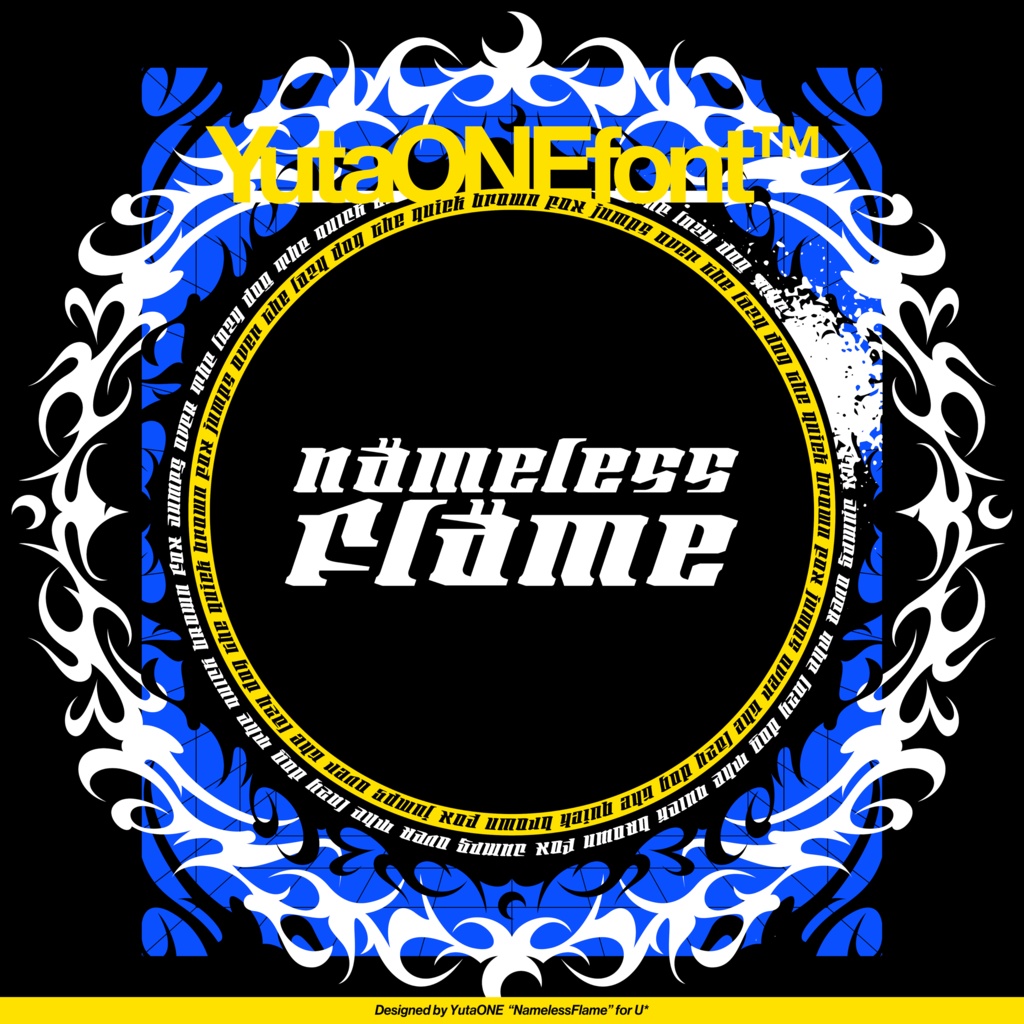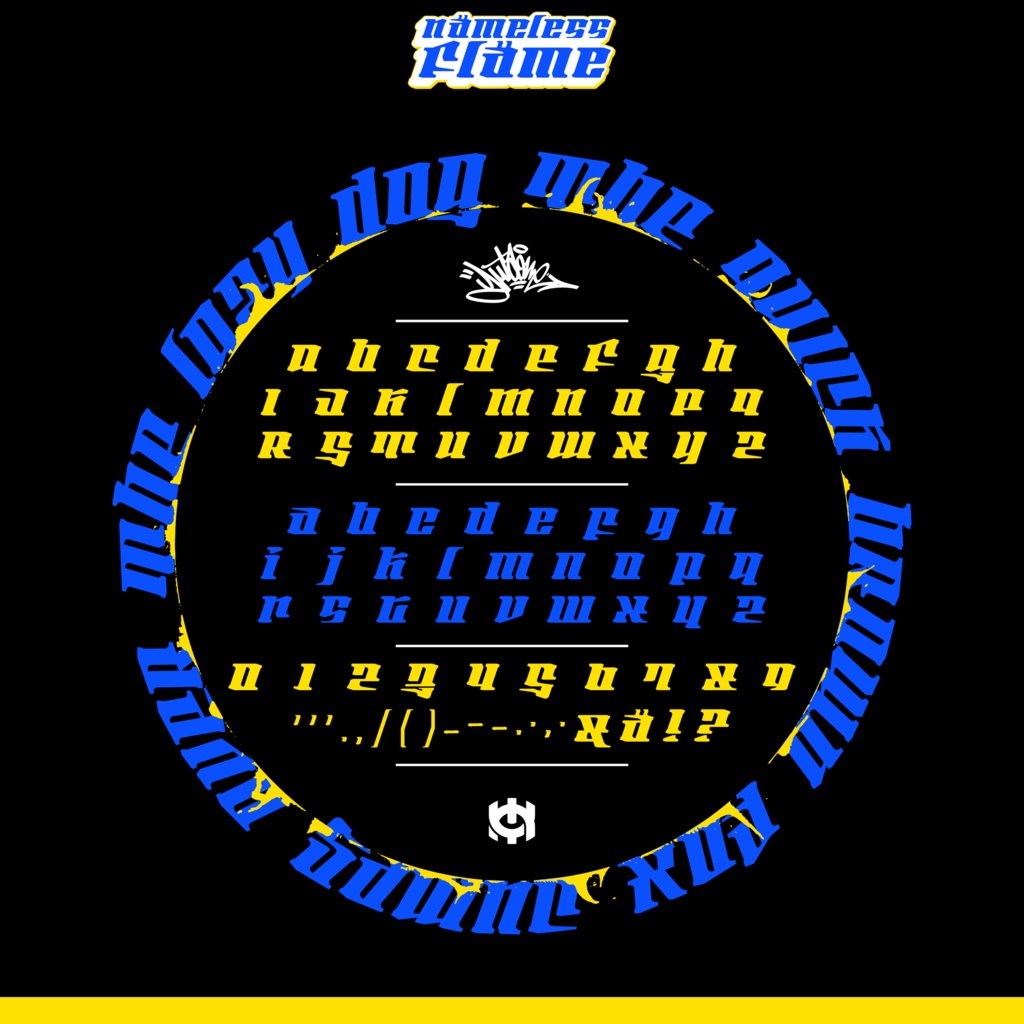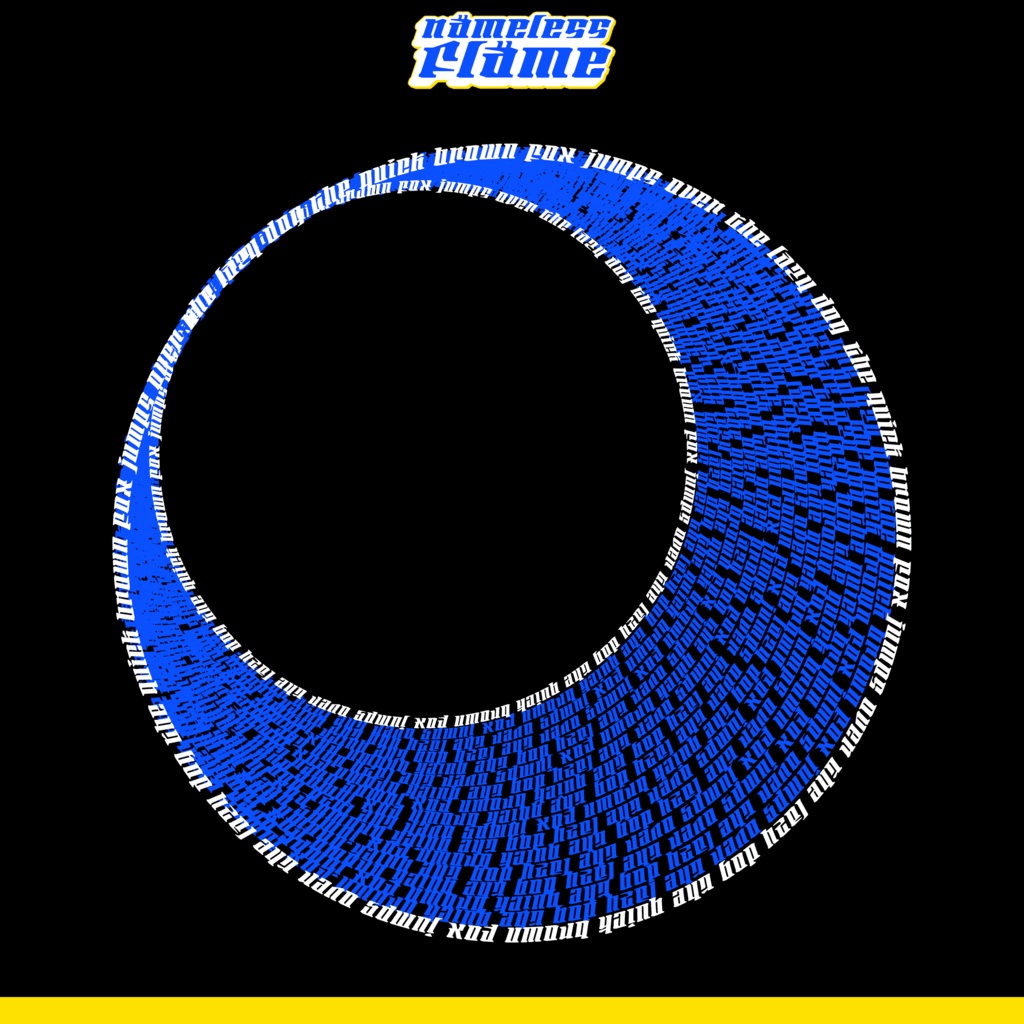
ネームレスフレイム(NamelessFlame)|Unnämed採用 タイプフェイス|ゆうたONEフォント™︎
Unnämed関連のグラフィックデザイン用に製作したフォントです。 Unnämedに関するイベントやお祝い事の時に無料化します! ベースフォントはネオスラッシュゴス https://yutaone.booth.pm/items/3830724 ◣◥◣フォントの利用規約◥◣◥ 当フォントは購入したしない問わず「ゆうたONE」と「Unnämed」をフォローしていない方の商用利用を禁じています。 未フォローの場合、または何らかの理由でフォローができない場合は、商用、非商用に関わらず、個人的に又は家庭内その他これに準ずるクローズドな範囲での利用に留めてください。 ーーーゆうたONEーーー ◆エックス https://x.com/yuta_ptv ◆スレッズ https://www.threads.net/@yuta_ptv_jp ◆インスタグラム https://www.instagram.com/yuta_ptv_jp/ ーーーーーーーーーーーー ーーーUnnämedーーー ◆エックス https://x.com/unnamednow00 ーーーーーーーーーーーー フォロワーの方であれば、個人利用・商用利用にかかわらず自由に使用することができます。企業や法人の場合でも同じです。 Unnämed公式と誤認させるような使用方法は禁止です。 クライアントワークはもちろん、ご自身や自社のオリジナルグッズ制作、同人誌、二次創作活動、アダルトコンテンツ、BL・GL・HL問わず、犯罪とされる用途以外のあらゆる題材に利用可能です。 また、著作権を放棄しているわけではないため、書体の利用を制限するような行為、及びフォントに含まれる書体の原型を保ったロゴデザイン等の商標登録は禁止です。 その他、作者を偽る、フォントデータ自体を二次配布または販売や転売する行為は禁止です。 ゲームやアプリ等、フォントデータをシステムに組み込む場合は第三者が吸い出せない形での利用をお願いします。 上記SNSにフォントを利用する制作物を投稿する場合は、可能な限りゆうたONEとUnnämedをフォローしているアカウントで公開してください。 ※フォントのインストール・ソフトでの使用についてのサポート・お問い合せは受け付けません。また、当フォントを使用して生じたいかなる損害につきましても当方は一切の責任を負わないものとします。 These fonts are free to download. You can also use them for your business by following the YutaONE account. If you do not follow us, please use them in a closed area. (X: @yuta_ptv|Instagram&threads: @yuta_ptv_jp) ーーーゆうたONEフォント™︎に関するよくある質問ーーー https://docs.google.com/document/d/1jzKjcBY7Kni8GaGqFhJaeS2VThokrYWUysKsHnFCxhQ/edit?usp=drive_link ーーーーーーーーー ※ゆうたONEが必要と判断した場合には、あらかじめ通知することなく、いつでもゆうたONEフォントの利用規約を変更することができるものとします。 ◣◥◣商品に関する注意事項◥◣◥ MacOSとAdobeソフトの組み合わせ以外での実機テストはしておりません。あくまで当フォントは「実用品の販売」ではなく「ゆうたONEの制作物に金銭的な価値をつけて応援ができる商品」です。動作の不具合については基本的に対応できませんのでご理解いただいた上でご購入ください。 ギンプやインクスペース等のグラフィックソフトだと、フォントファミリーが分割されず1つのフォントだと認識されてしまい、グラフィックソフト内のフォントブックに表示されないトラブルが確認されています。お手数ですが使用したいフォントのみをインストールする、もしくはフォント名称をそれぞれ別名に書き換えてインストールしていただきますようお願いします。(いずれソフト側が対応してくれるものと思います)